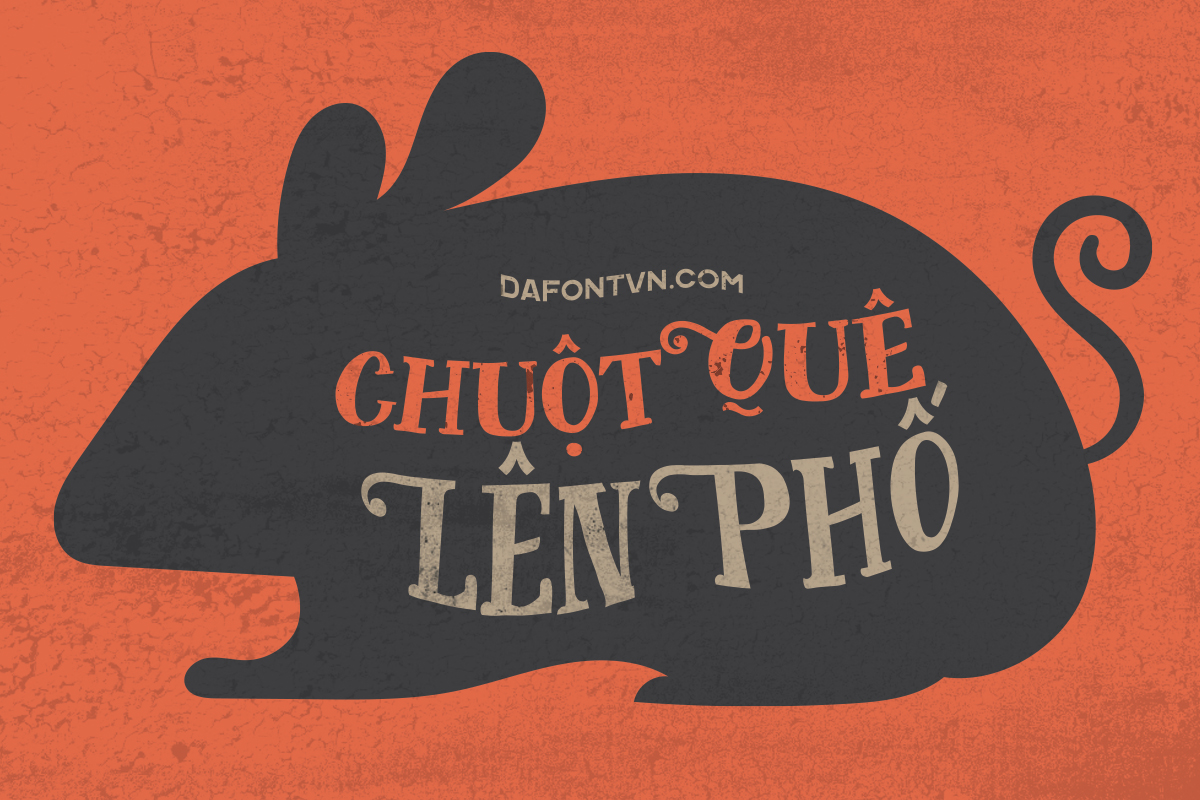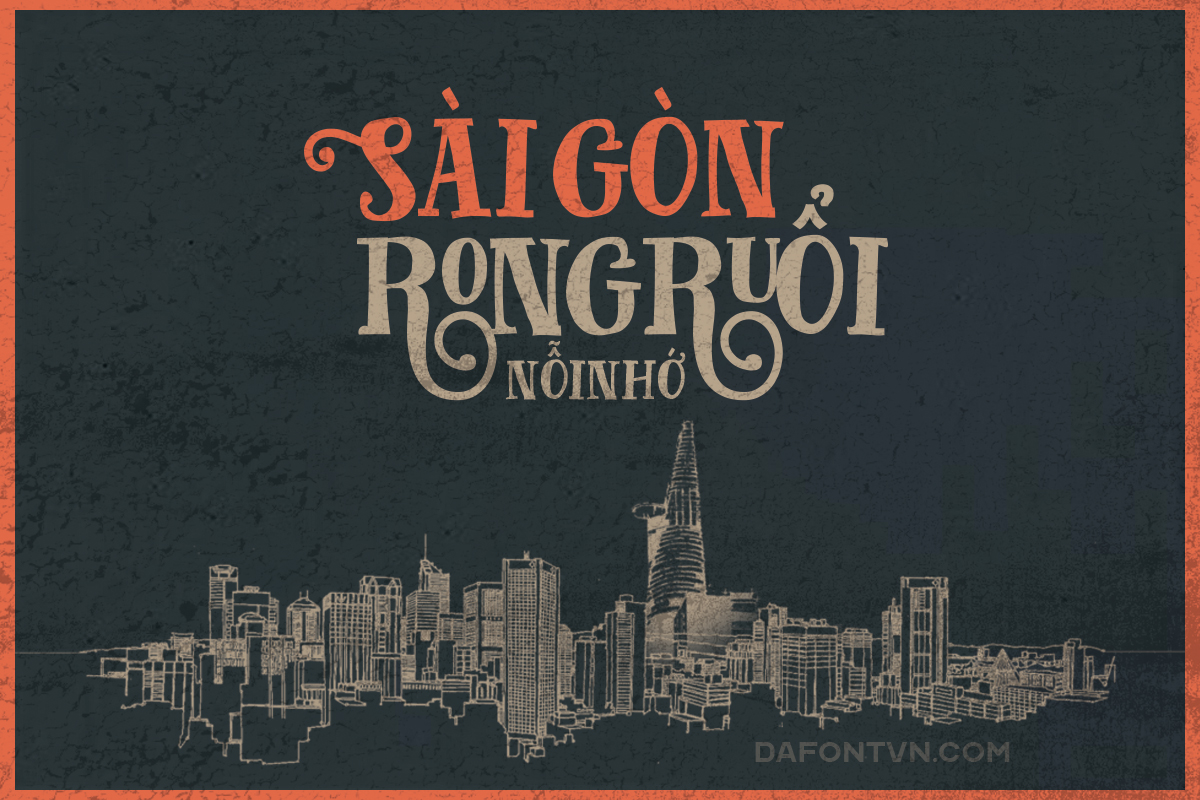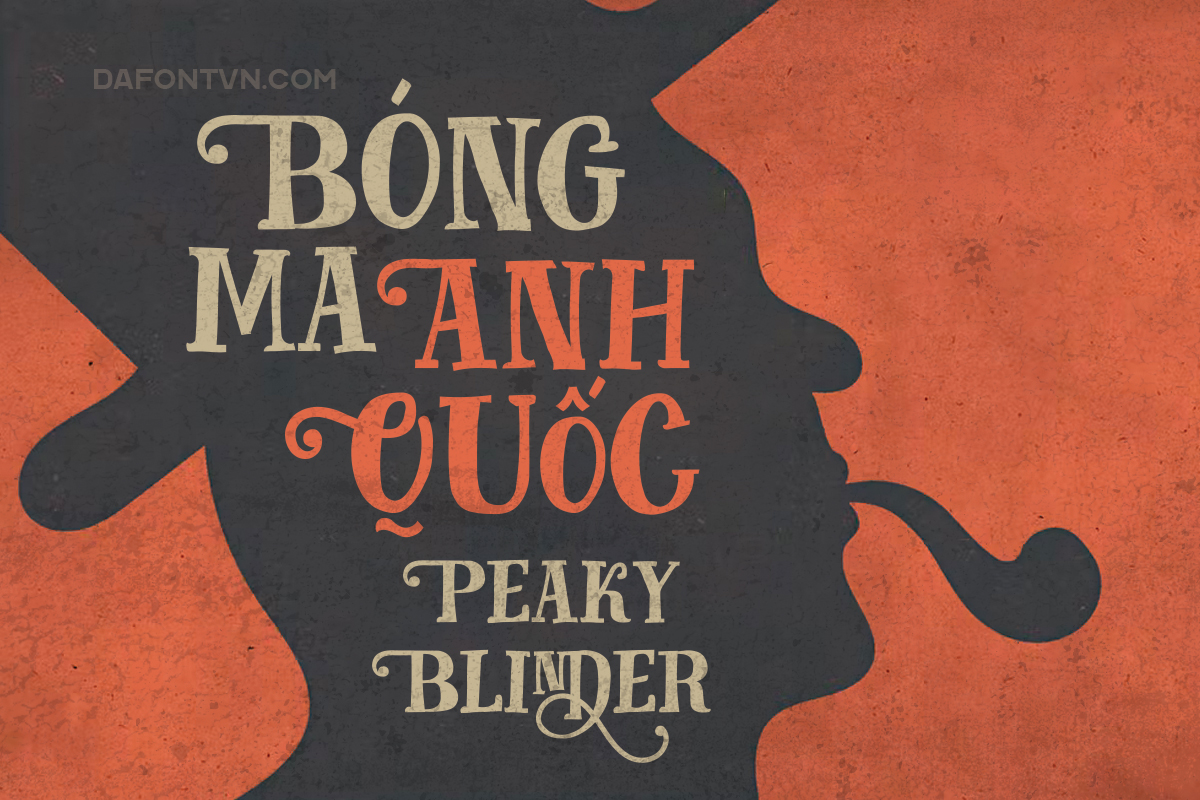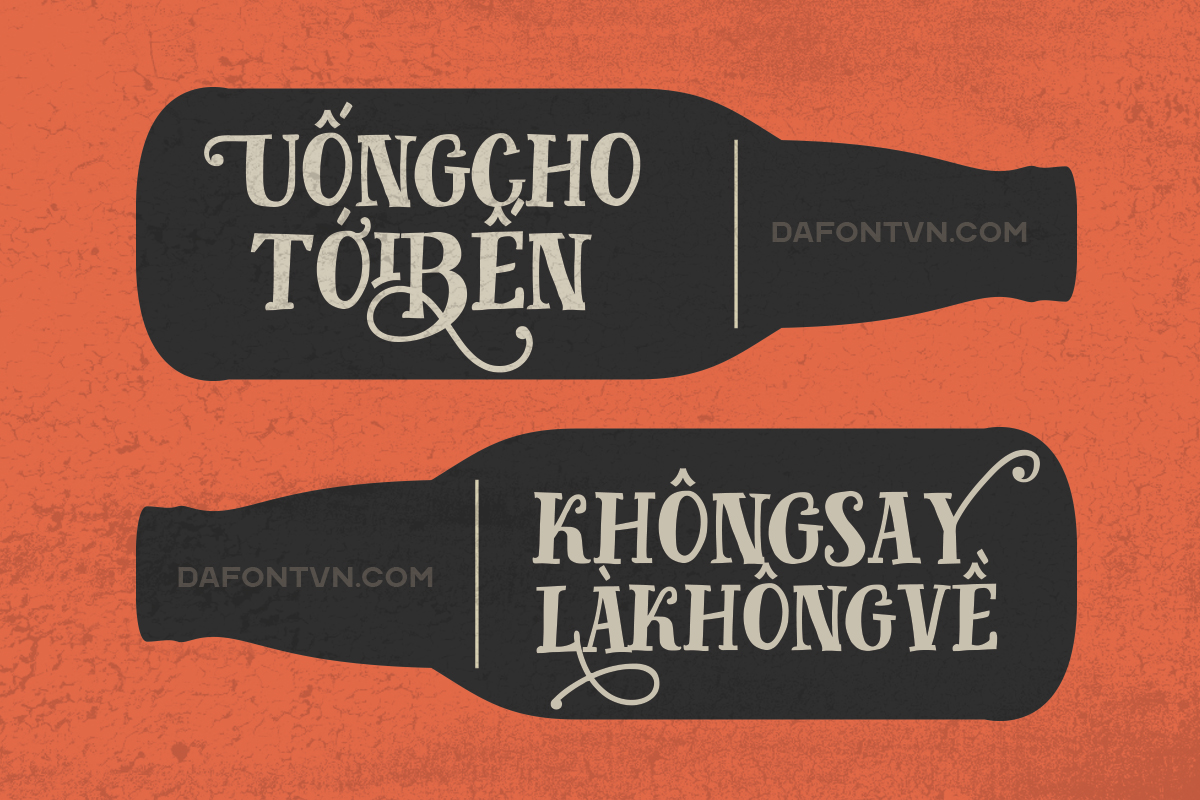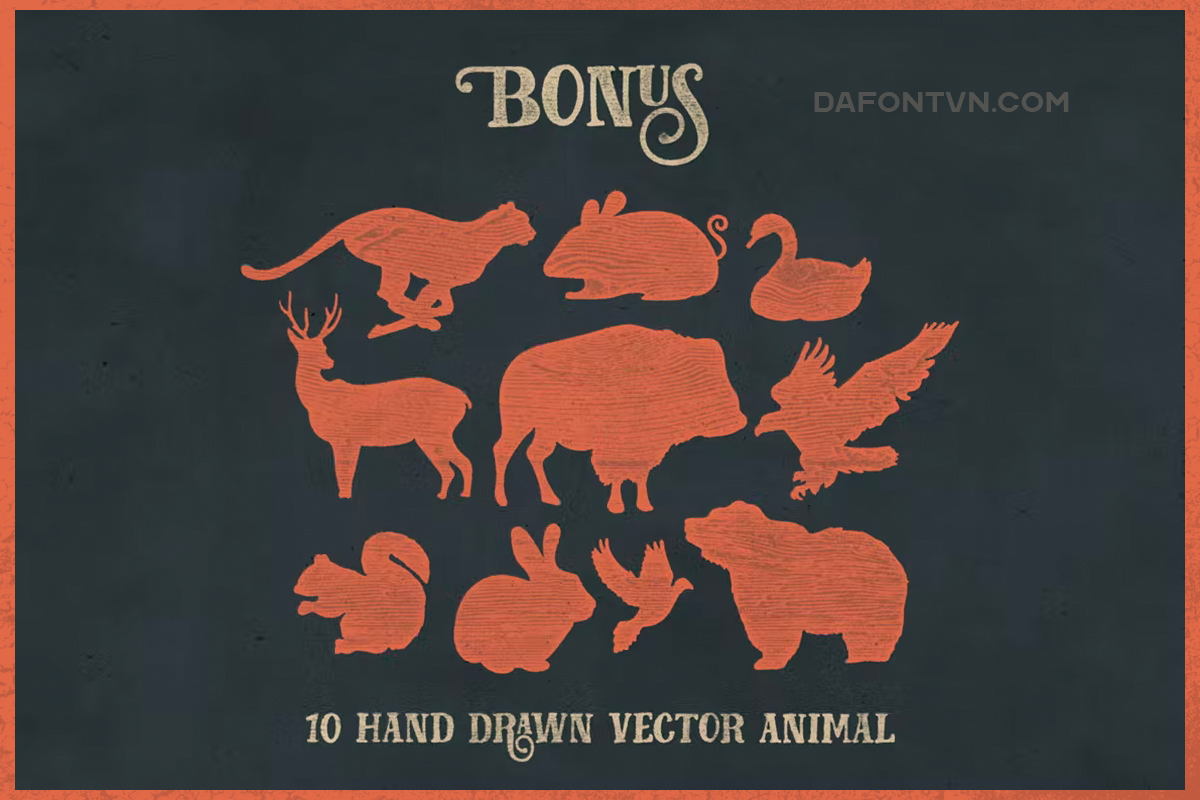
Font iCiel Fairy Tales việt hóa + Bonus
Font Fairy Tales việt hóa một phông chữ viết tay lấy cảm hứng từ các quảng cáo cổ điển và áp phích phim thời xưa. Mặc dù nó phù hợp cho các mục đích khác nhau như tiêu đề, thiệp mời, bìa truyện, poster… Với sự kết hợp cổ điển và các tính năng OpenType được kết hợp với nhau, bạn có thể dễ dàng tạo ra các thiết kế ấn tượng cho riêng mình.
Font Fairy Tales có 231 glyph và các ký tự thay thế tuyệt đẹp bạn có thể sử dụng trong các phần mềm hỗ trợ OpenType như Photoshop, Illustrator hoặc InDesign. Ngoài ra Bonus kèm theo bao gồm 10 động vật vector vẽ tay với định dạng .AI và .EPS